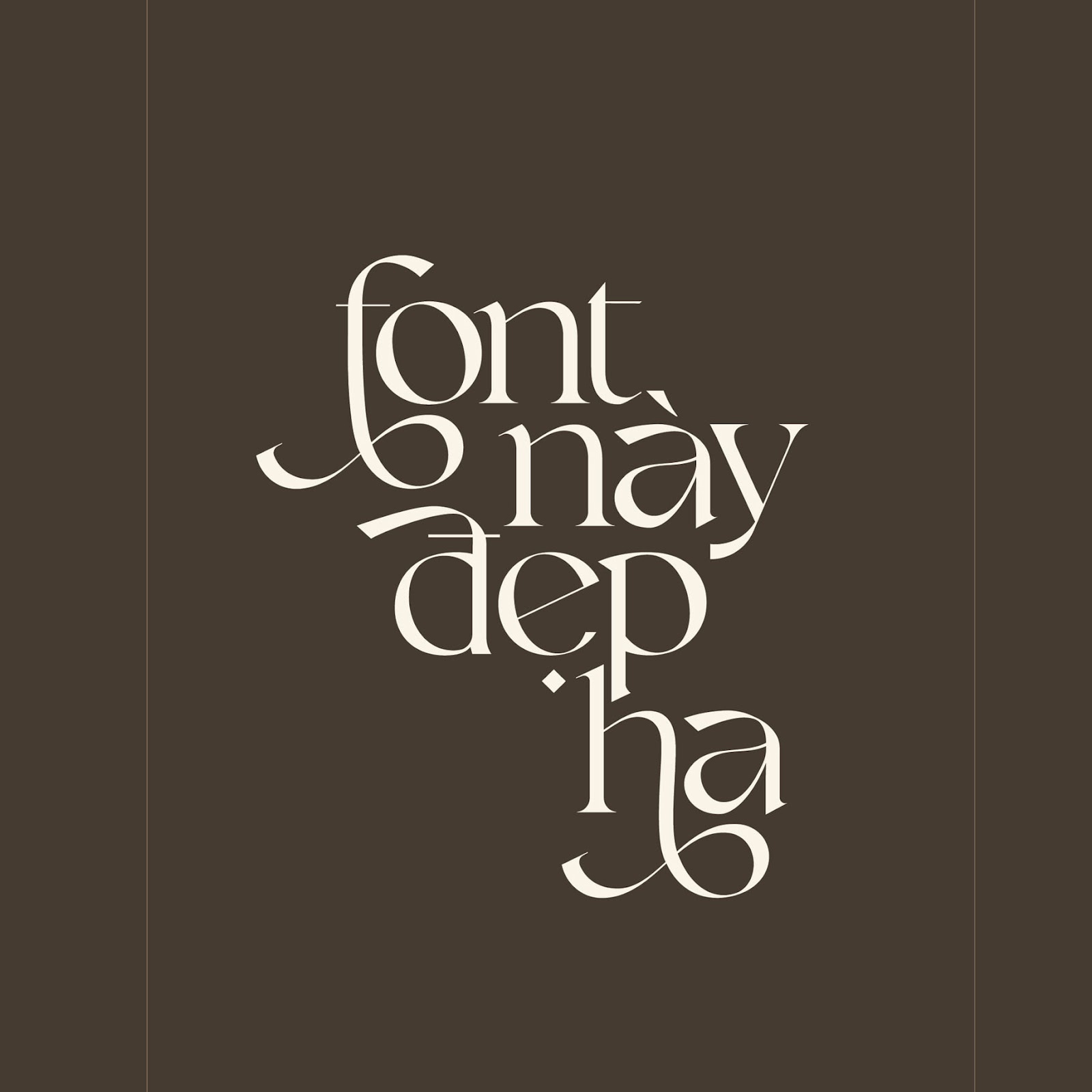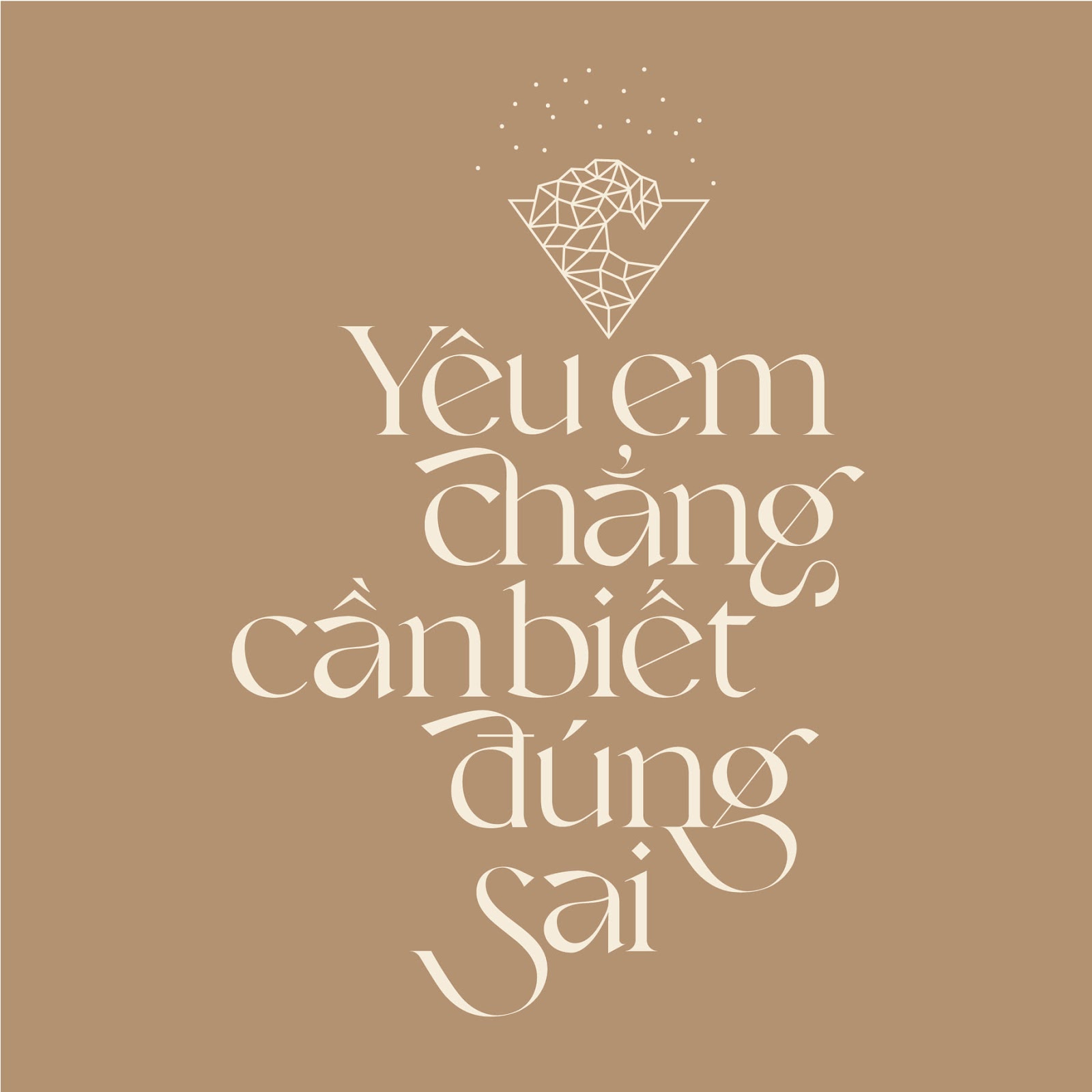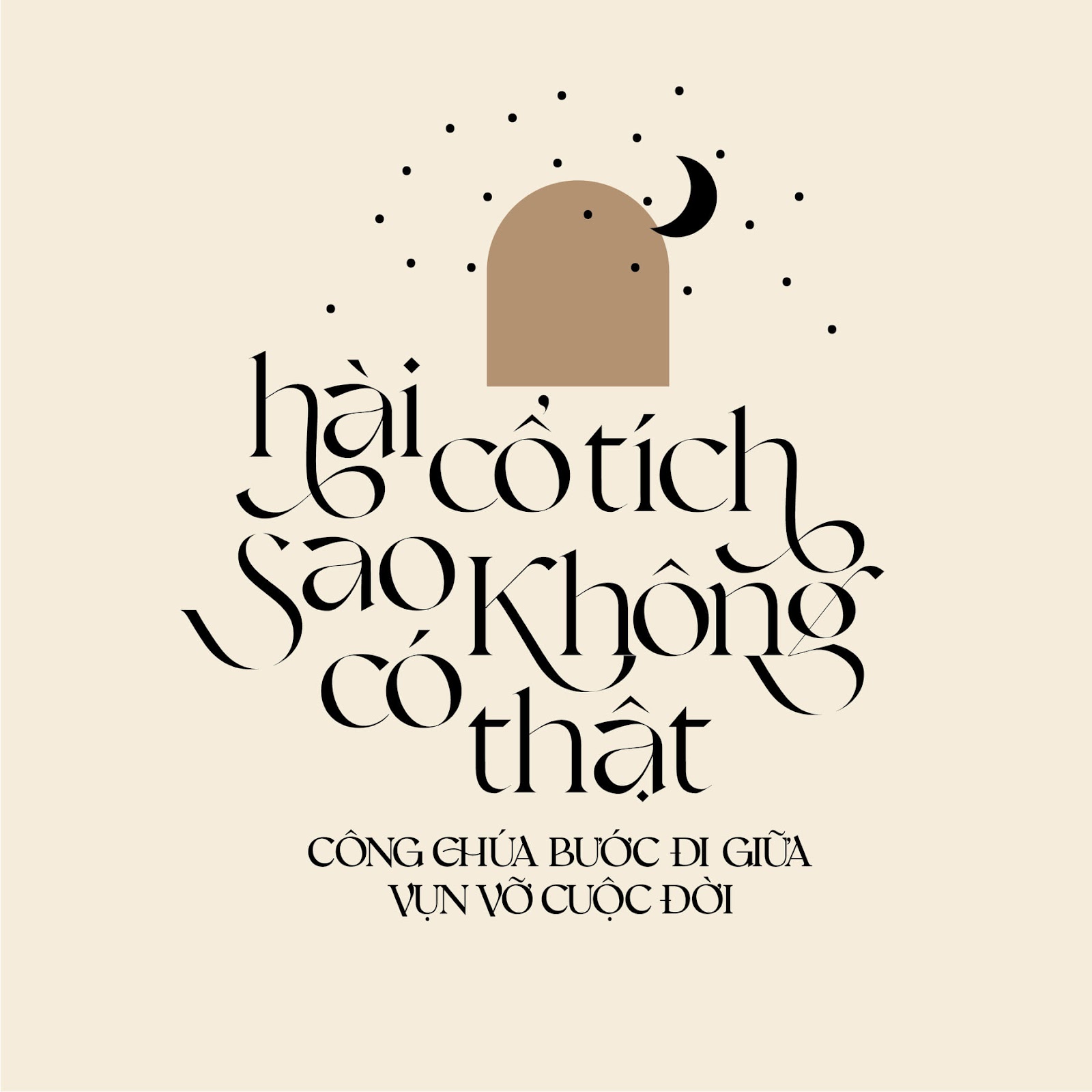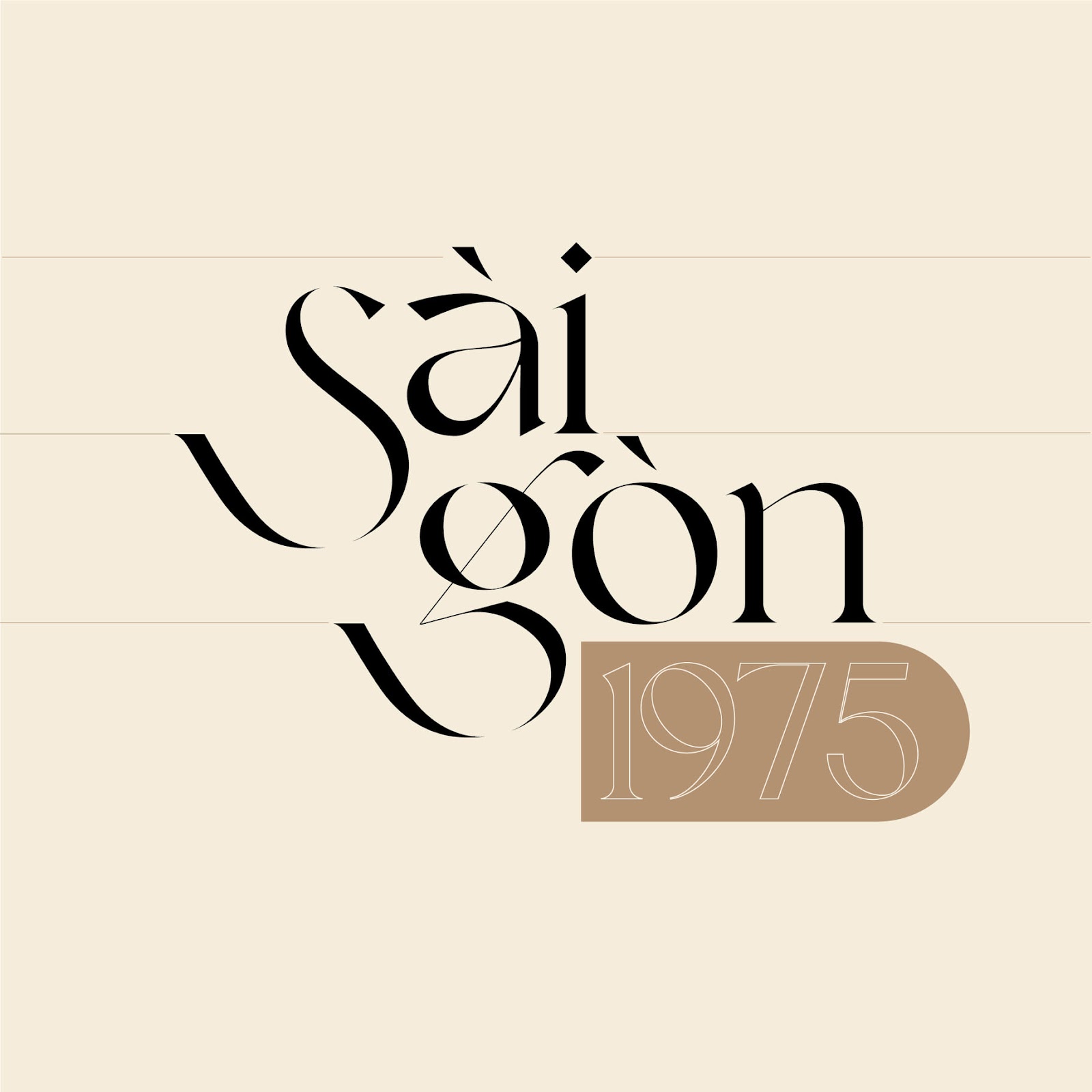
Tải trọn bộ font Valky Việt hóa cực xịn
Valky Classic Modern Typeface là một kiểu font serif cổ điển và hiện đại được thiết kế lạ mắt với các chữ ghép đẹp, rất nhiều glyph thay thế đặc biệt. Đây là một font chữ rất linh hoạt ở các text kích thước nhỏ cho đến lớn. Phù hợp cho các dự án xây dựng thương hiệu, tạp chí, bao bì sản phẩm…
Bộ font việt hóa Valky bởi MTD bao gồm 4 kiểu:
• Valky Light
• Valky Regular
• Valky Bold
• Valky Semibold